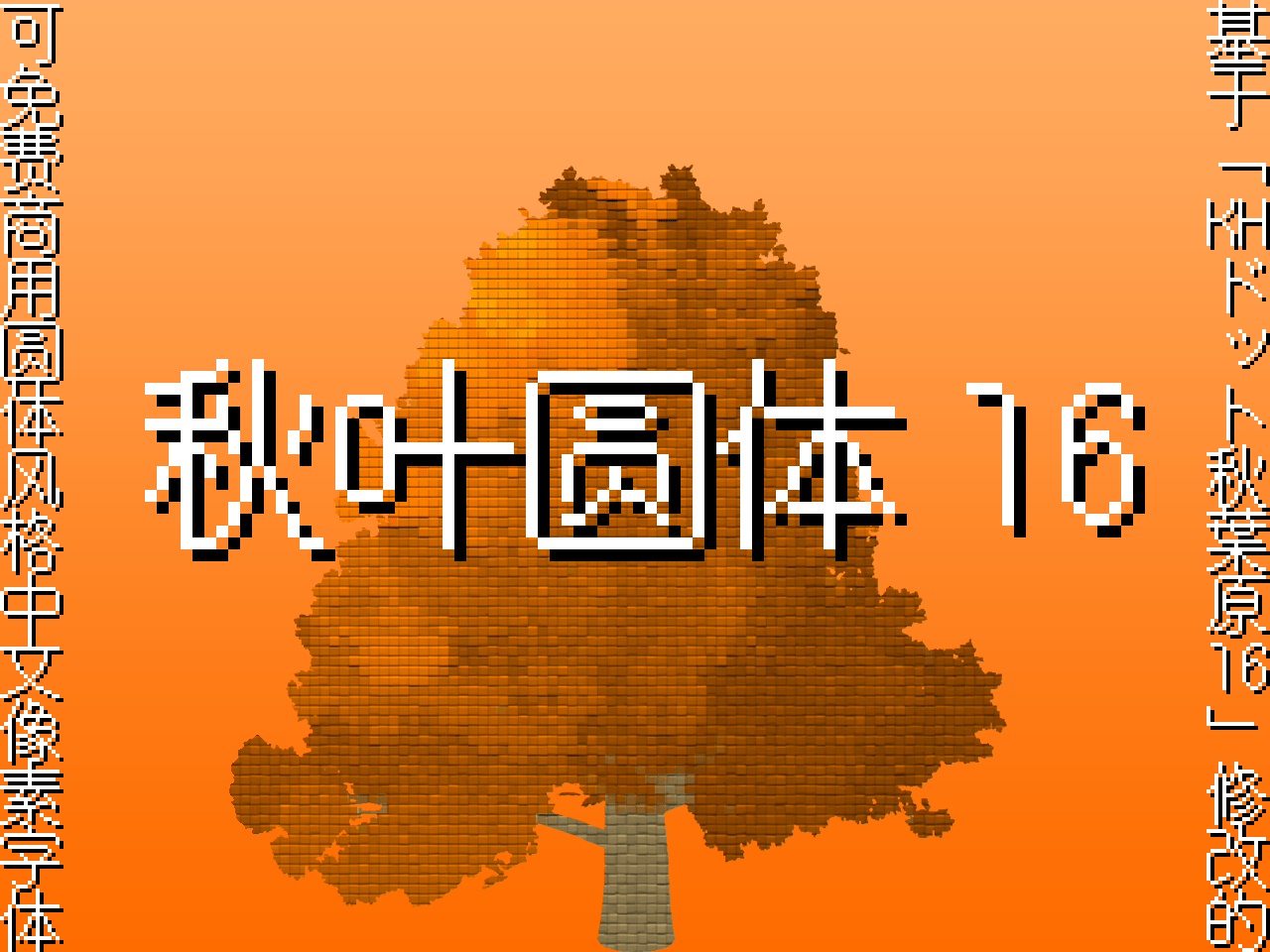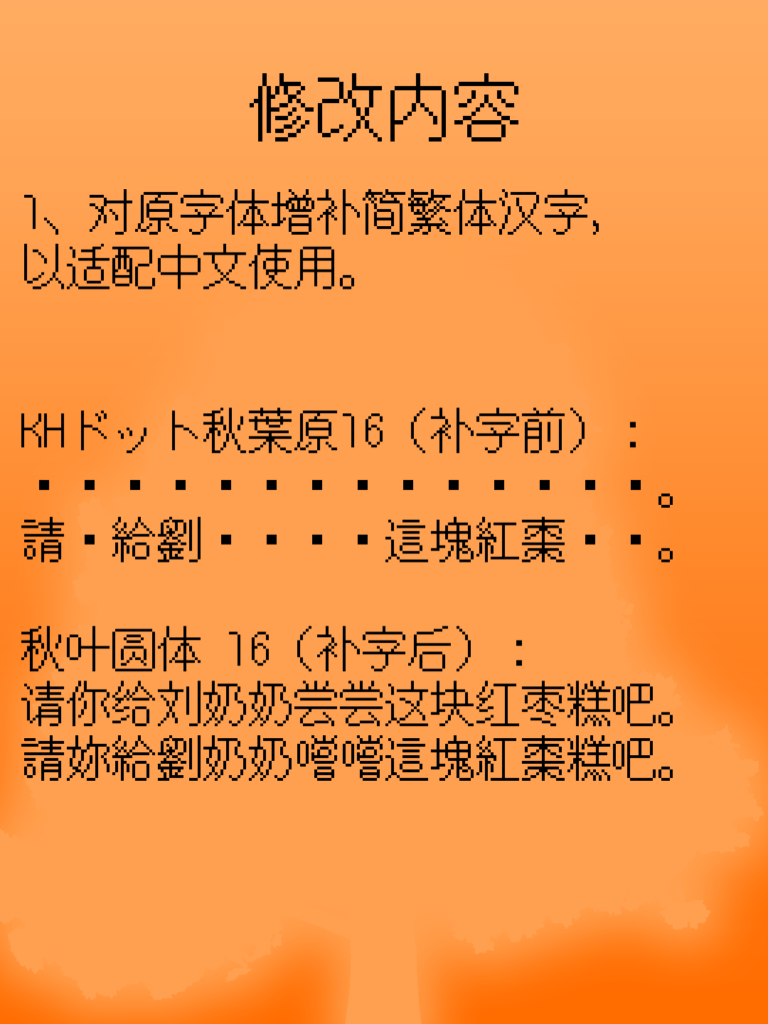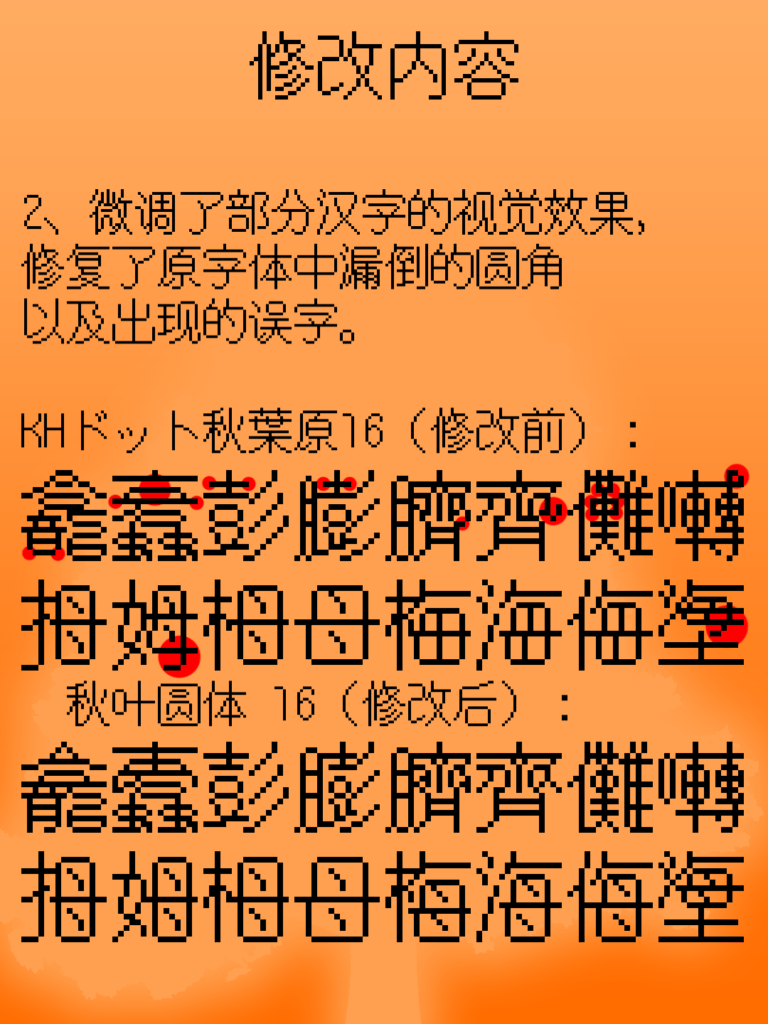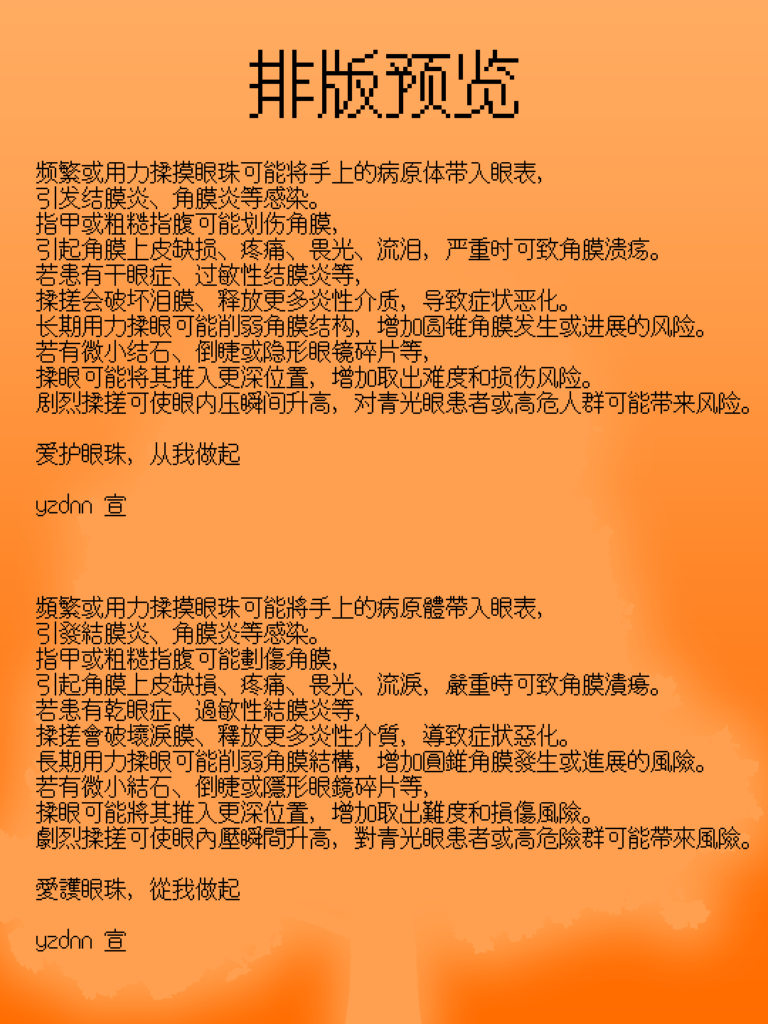
「秋叶圆体 16」是基于「KHドット秋葉原16」增补简繁体汉字的16px点阵圆体,适合在各种像素风场景使用。
中文像素字体长期缺少圆体风格的字体,本补字项目为填补此空白而诞生。
于是,在经过将近两个月的调整和补字后,总算是发布了第一个版本。
与原字体相比,本字体修复了错误的字形,为保持视觉平衡略微扩大了中宫,且尽可能倒圆了包括竖提在内所有边角,仅剩下部分角度过小难以倒圆的锐角维持了原设计。
希望这款字体能为像素艺术创作和游戏本地化工作添砖加瓦。